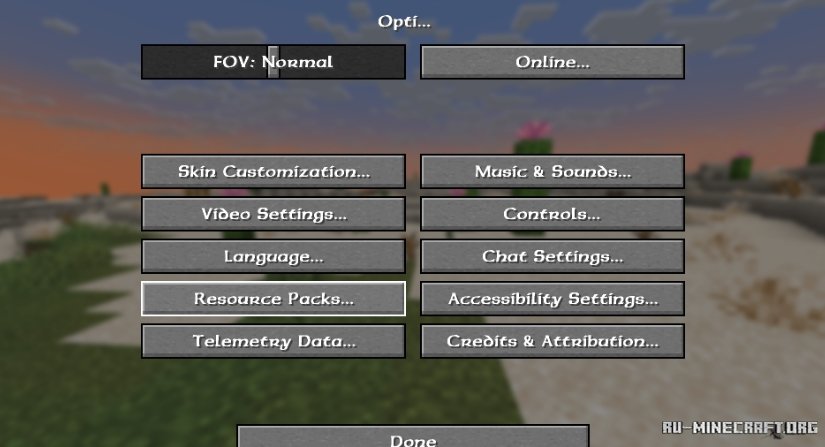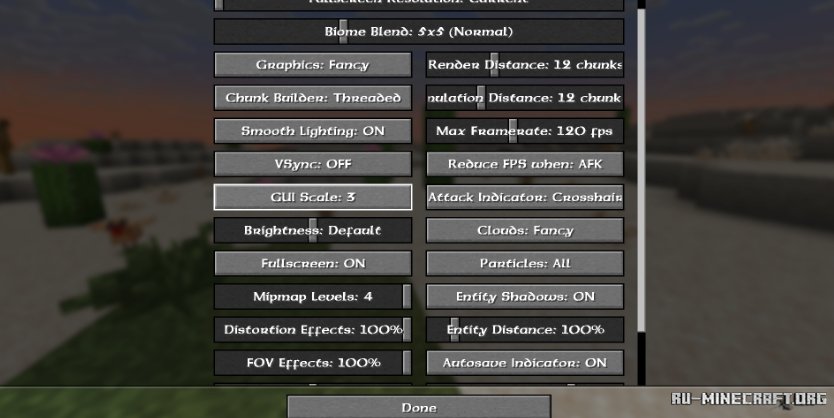
Неплохой пакет текстур Link’s RPG Font, благодаря которому вы сможете изменить привычный шрифт вашего майнкрафта, вы сможете ввести некий эффектный шрифт в стилистике RPG игр. Весьма интересное визуальное улучшение подобного формата, которое непременно сможет понравиться - оцените бесплатно пакет.